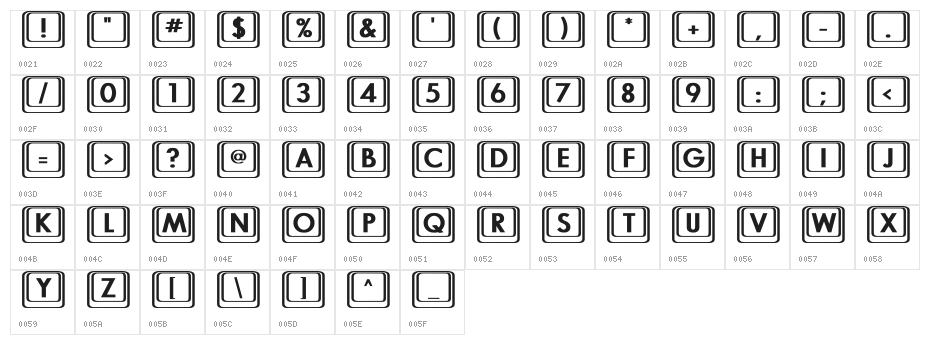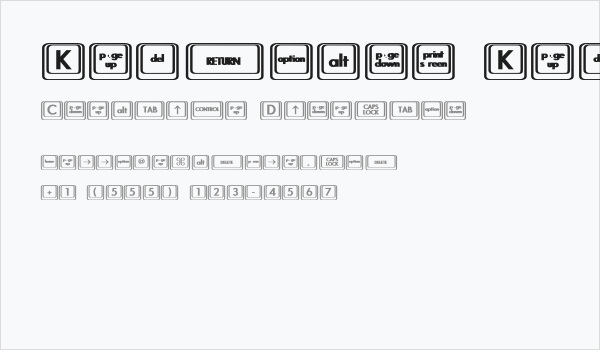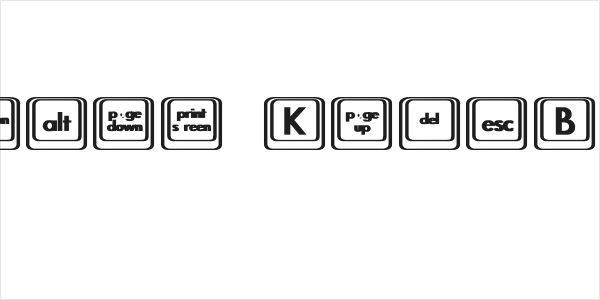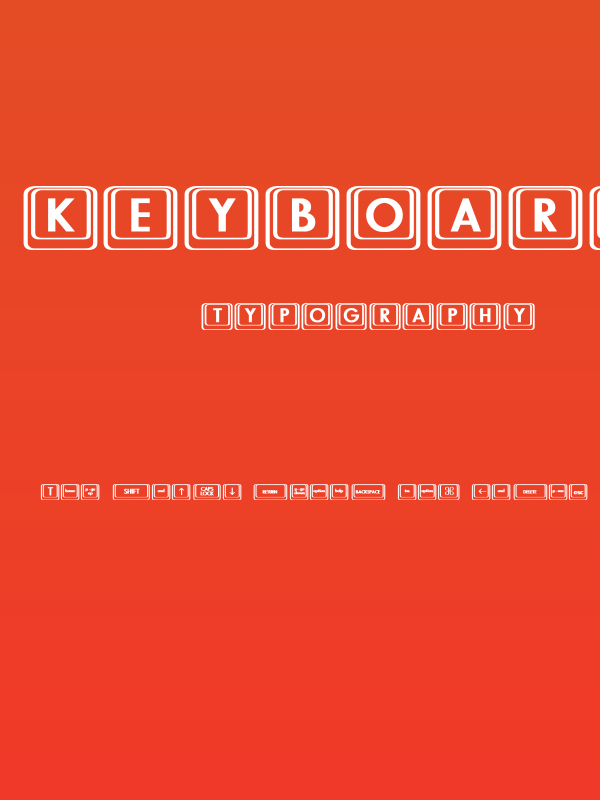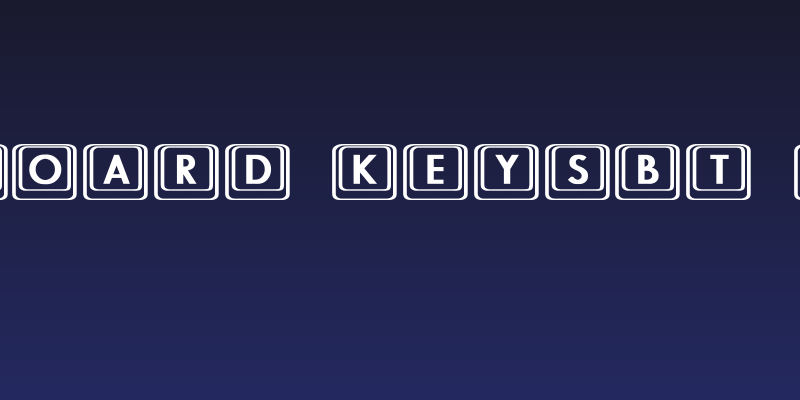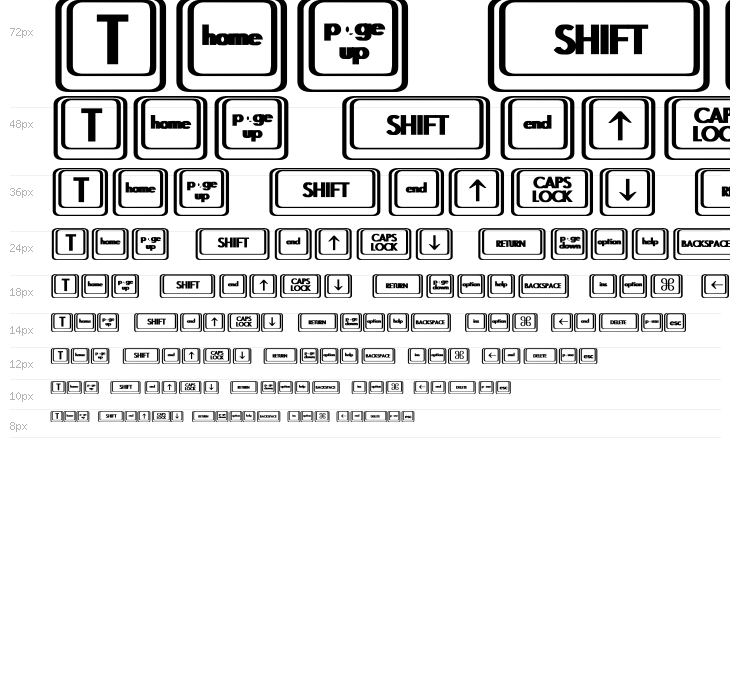
Keyboard KeysBT Bold Font
| Caso d'uso | Logos, Headlines, Digital Interfaces |
| Progetti proposti | Ideal for tech-related designs, digital interfaces, educational materials, or any project needing a modern, digital look. |